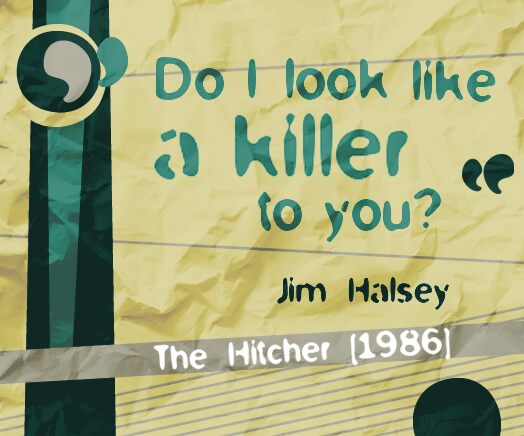
McKoy to bezpłatny, organiczny font typu display o swobodnym, wycinanym ręcznie charakterze. Litery wyglądają na miękkie i pełne, by nagle zwęzić się lub złamać w drobne nacięcia i uszczerbki. Nadaje to krojowi zabawnego, lekko zużytego rytmu, który kojarzy się z stylem retro, ale nie jest przypisany do jednej konkretnej epoki.
Pasuje do muzycznych ulotek, opakowań zabawek, okładek zinów, szyldów sklepowych i krótkich projektów logo, w których kształty mówią same za siebie. Jako darmowy font, McKoy sprawdza się również w tytułach i dużych cytatach – zwłaszcza gdy potrzebujesz wyrazistych liter, które sprawiają wrażenie swobodnych, nieoczywistych i niepodrabialnie ręcznych.